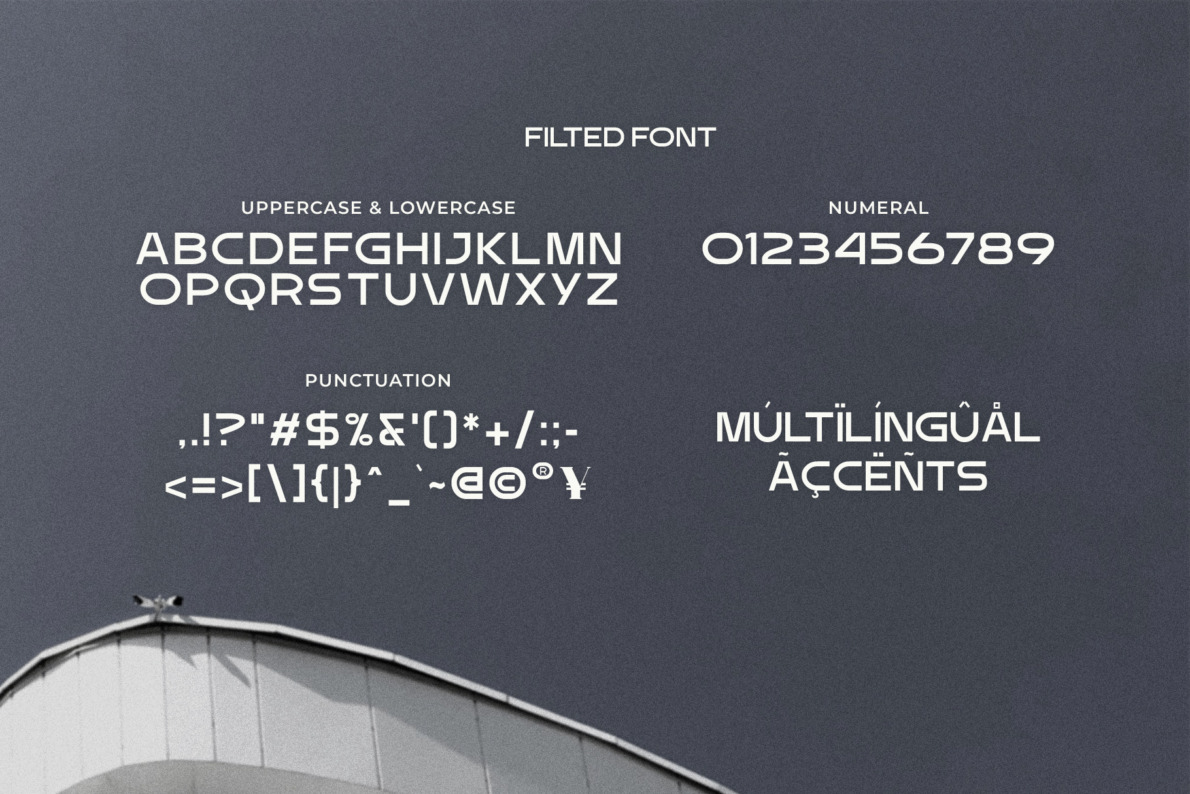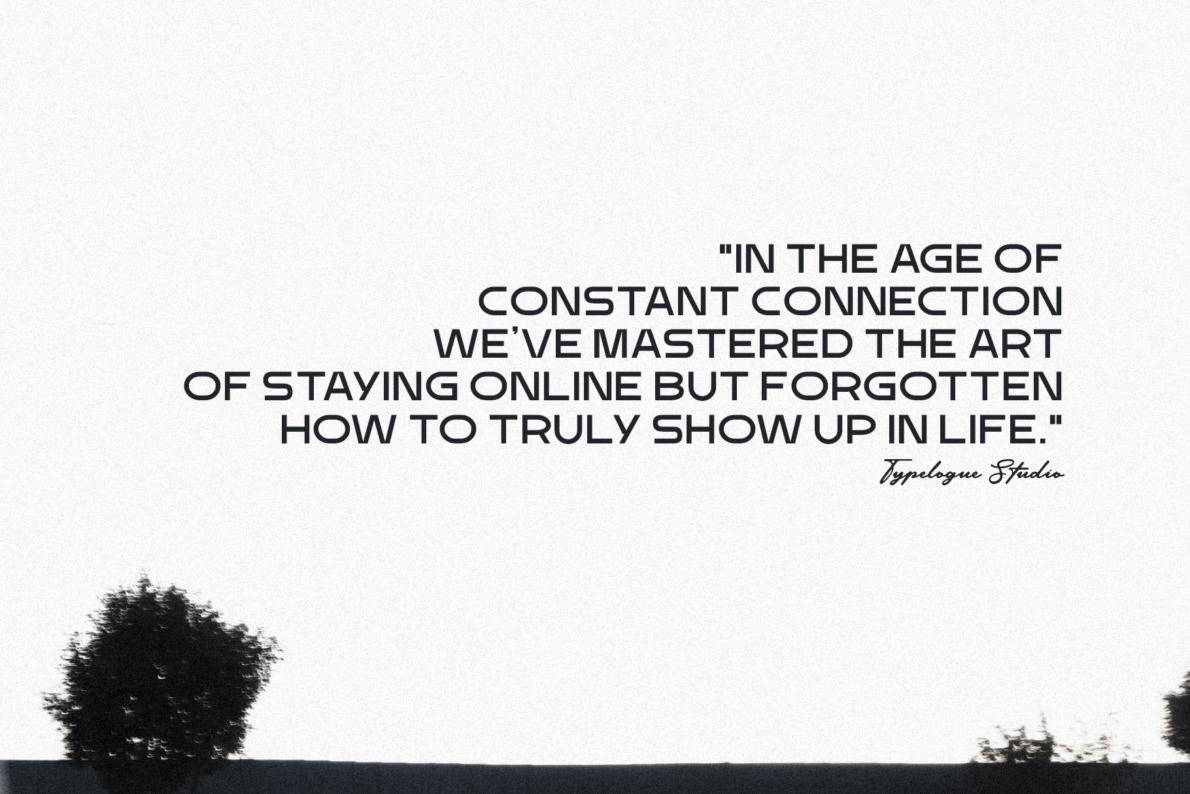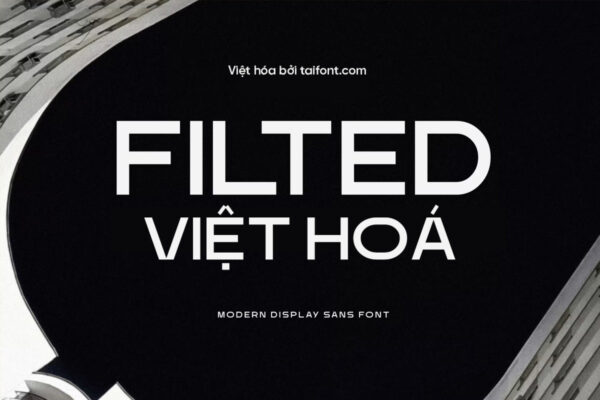
Giới thiệu về Font TF Filted Việt hóa
TF Filted Việt hóa là một font chữ không chân (sans-serif) nổi bật với thiết kế sắc nét, hiện đại và cực kỳ rõ ràng, lý tưởng cho mọi ấn phẩm cần sự chuyên nghiệp và dễ đọc. Font này toát lên vẻ tinh tế, gọn gàng và một chút phong cách tối giản, phù hợp để thu hút mọi ánh nhìn và khẳng định sự chuyên nghiệp trong từng dòng chữ.
Với đặc điểm là nét không chân hiện đại, tính thẩm mỹ cao và khả năng ứng dụng đa dạng, Filted là lựa chọn hoàn hảo cho các thiết kế muốn truyền tải sự hiện đại, mạnh mẽ và sự độc đáo, đặc biệt là trong lĩnh vực in ấn:
- In ấn chuyên nghiệp: Hoàn hảo cho các ấn phẩm in ấn đòi hỏi sự rõ ràng và chất lượng cao như tạp chí, sách, báo cáo, brochure, catalogue, thiệp mời, bao bì sản phẩm, hoặc danh thiếp. Độ sắc nét và dễ đọc của font giúp nội dung được truyền tải một cách hiệu quả, ngay cả trên nhiều chất liệu giấy khác nhau.
- Tiêu đề và Nội dung: Rất phù hợp cho cả tiêu đề chính (headline) và nội dung bài viết, đảm bảo tính đồng nhất và chuyên nghiệp cho toàn bộ ấn phẩm. Font này giúp người đọc dễ dàng tiếp thu thông tin.
- Thiết kế nhận diện thương hiệu: Lý tưởng cho logo, tagline hoặc bộ nhận diện thương hiệu của các công ty, doanh nghiệp muốn truyền tải sự hiện đại, uy tín và sự đáng tin cậy. Filted giúp xây dựng một hình ảnh thương hiệu vững chắc và dễ nhận diện.
- Thiết kế kỹ thuật số: Ngoài in ấn, font này cũng rất phù hợp cho các giao diện người dùng trên website hoặc ứng dụng, mang lại trải nghiệm đọc mượt mà và chuyên nghiệp trên màn hình.
Với TF Filted Việt hóa, bạn có thể dễ dàng thổi hồn tinh tế, hiện đại và vẻ đẹp rõ ràng vào các thiết kế, tạo ra những sản phẩm không chỉ đẹp mắt mà còn cực kỳ ấn tượng và có khả năng thu hút sự chú ý tối đa.
Font Việt hóa TF Filted